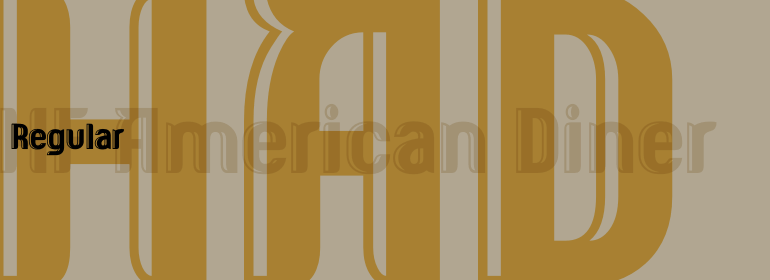
HF American Diner
HF American Diner,这款字体结构工整、笔画清晰,兼顾美观与易读性,适用于标题、正文、海报、包装、LOGO 等多种场景。字形优雅稳定,风格百搭耐看,适配日常排版与创意设计,让文字呈现更舒适、更具质感。HF American Diner一笔一画,皆是细节,以均衡的比例、流畅的线条打造舒适视觉体验,字形端正大气,风格简约现代。无论是商业设计、品牌宣传还是日常排版,都能轻松驾驭,让文字更有格调与力量。HF American Diner字体下载。